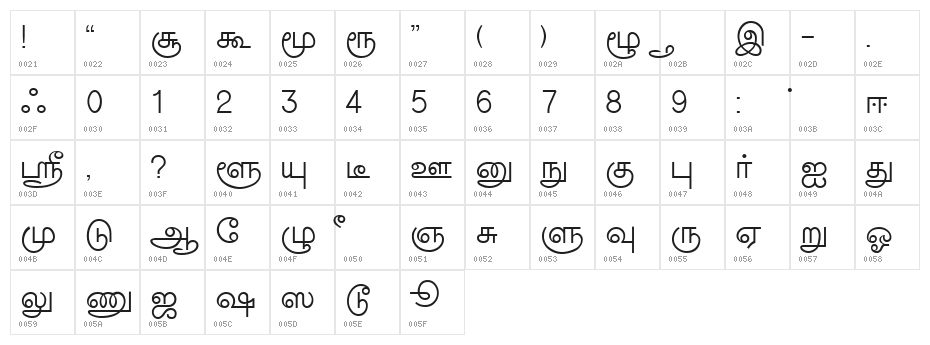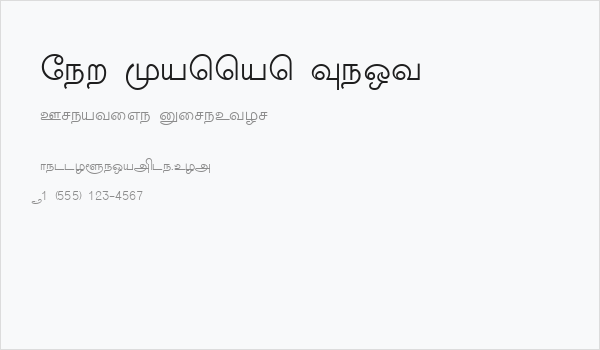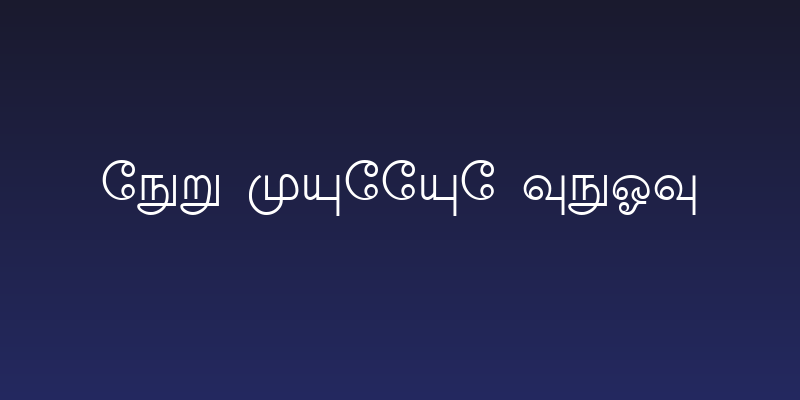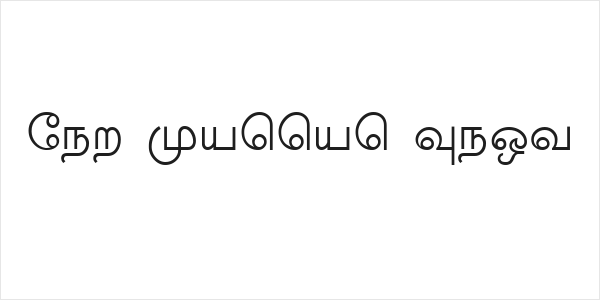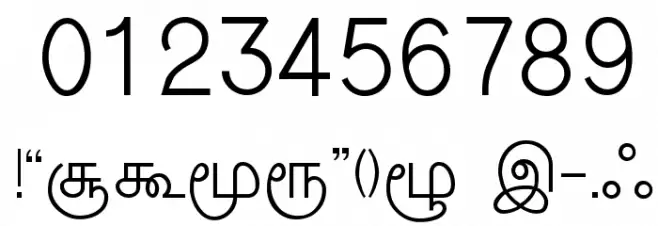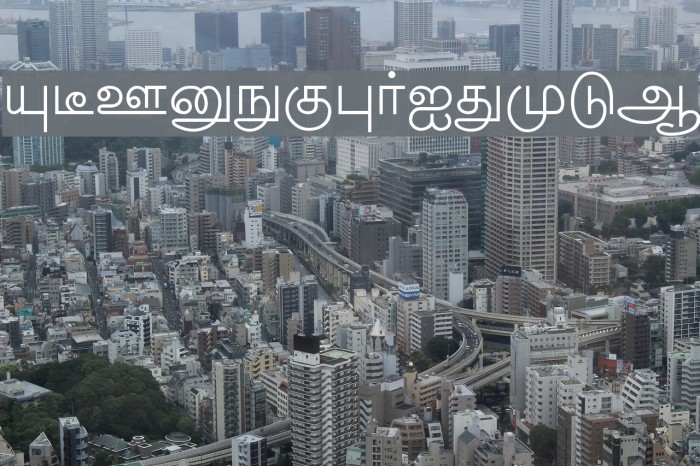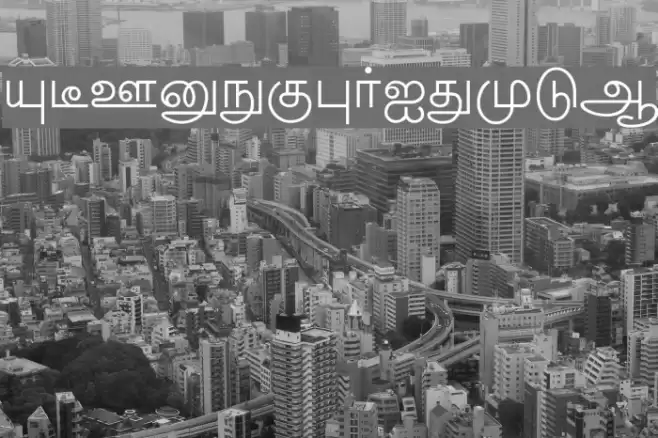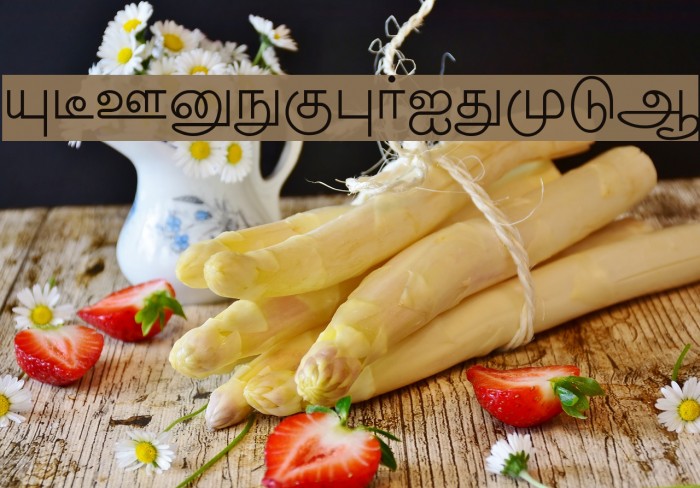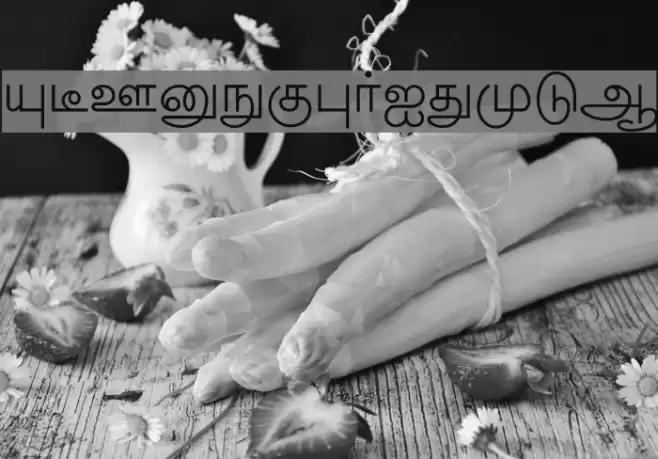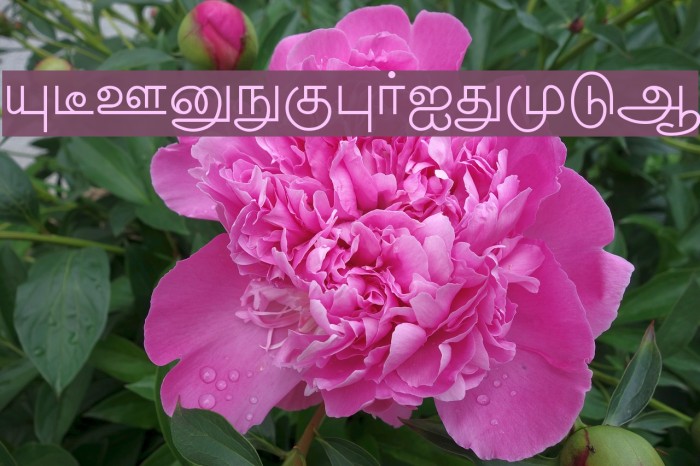
New Kannan Text Font
| Anwendungsfall | Body text, Digital content, Signage |
| Vorgeschlagene Projekte | Ideal for educational materials, digital content, signage, and branding projects requiring Tamil script. |